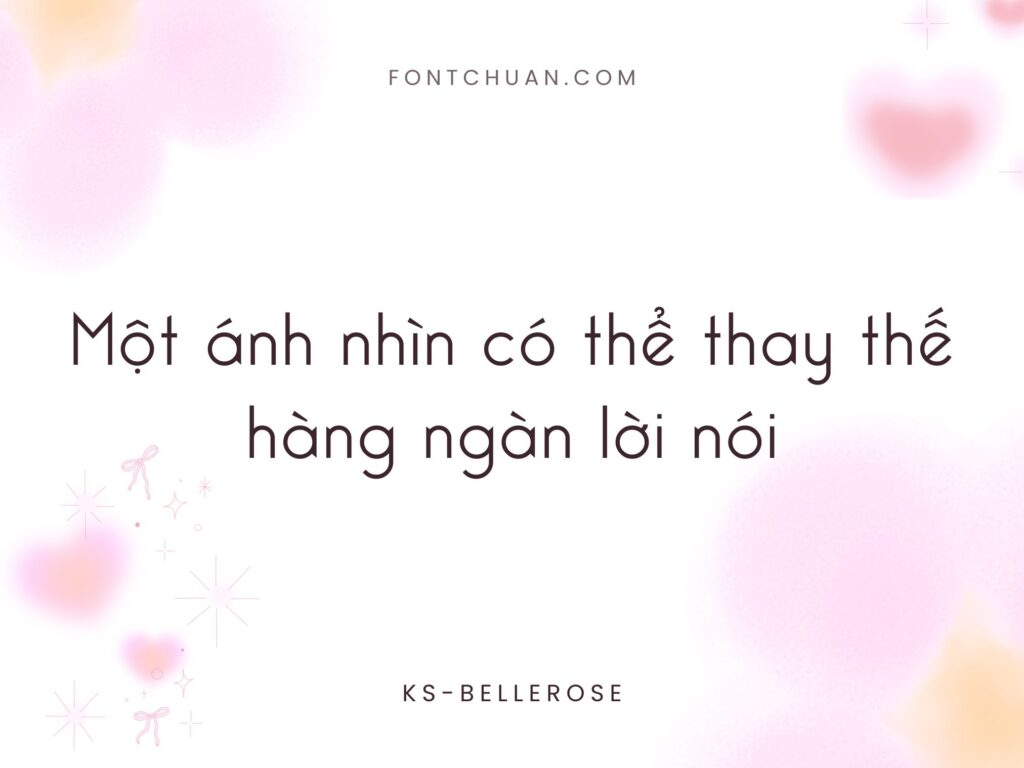
Bellerose là một phông chữ Font Display mang phong cách retro, được thiết kế bởi James M. Harris. Phông chữ này có các đường nét thanh mảnh và cong nhẹ, tạo nên vẻ đẹp cổ điển nhưng vẫn hiện đại. Với phong cách Art Deco đặc trưng, Bellerose thường được sử dụng trong các thiết kế mang tính hoài cổ và sang trọng. Phiên bản KS Bellerose đã được Việt hóa bởi Kiên Sinh, giúp hỗ trợ đầy đủ các ký tự tiếng Việt. Ngoài tiếng Việt, phông chữ này còn hỗ trợ nhiều ngôn ngữ khác, mở rộng khả năng ứng dụng trong các dự án thiết kế toàn cầu. Việc Việt hóa này đã được thành viên của Font Chuẩn chọn lọc và sưu tầm nhằm đáp ứng nhu cầu bạn đọc và giúp áp dụng vào các dự án thực tế.
Về đặc điểm thiết kế, Bellerose có cấu trúc sans-serif với các đường nét mềm mại và độ dày trung bình, mang lại cảm giác thanh lịch, cổ điển và rất phù hợp ứng dụng làm Font chữ thiệp cưới. Các chữ cái có độ cong nhẹ, giúp tạo sự mềm mại nhưng vẫn giữ được sức mạnh cần thiết cho các tiêu đề, logo và các ấn phẩm sang trọng. Với phong cách đặc trưng, Bellerose phù hợp cho các ứng dụng như thiết kế logo, biển hiệu, tiêu đề sách, poster cổ điển, bao bì sản phẩm và các thiết kế hoài cổ. Phông chữ này đặc biệt thích hợp với các lĩnh vực như quảng cáo, thiết kế thương hiệu, thời trang, ẩm thực và các dự án thiệp cưới sang trọng. Sự tinh tế của nó giúp dễ dàng hòa hợp với nhiều phong cách thiết kế khác nhau, từ cổ điển đến hiện đại, đồng thời mang lại nét đặc sắc cho các dự án nghệ thuật và thương hiệu.